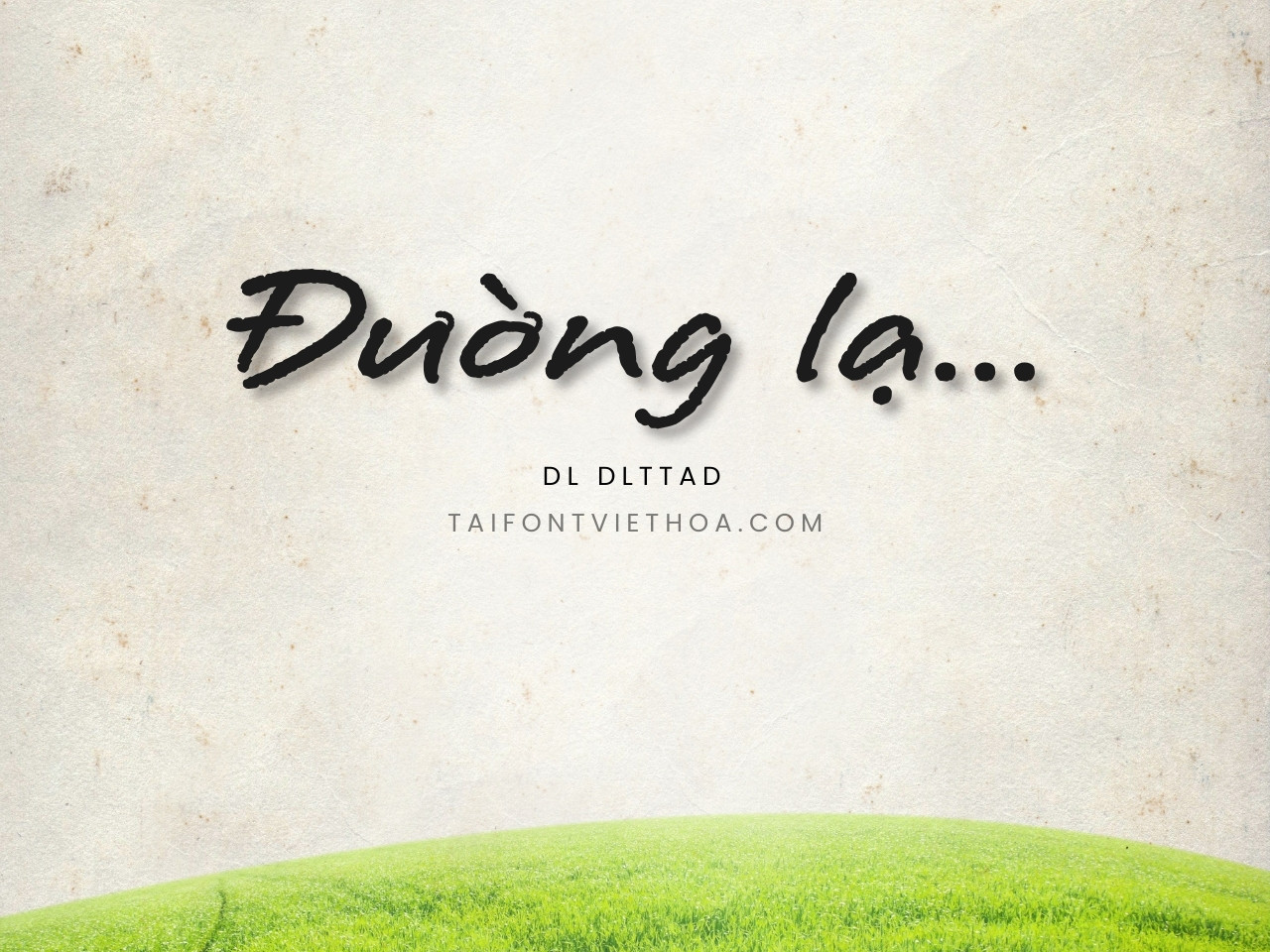
Giới thiệu về font DL Đừng Làm Trái Tim Anh Đau và bản Việt hóa
DL Đừng Làm Trái Tim Anh Đau là một font chữ viết tay (handwritten script) mang đậm dấu ấn tình cảm, được thiết kế theo phong cách cá nhân hóa với đường nét mềm mại, bay bổng như những lời nhắn nhủ ngọt ngào. Tuy không có bản gốc trên các kho font quốc tế, nhưng phiên bản này được phát triển và Việt hóa dành riêng cho người dùng Việt Nam, mang lại trải nghiệm trọn vẹn với bộ ký tự tiếng Việt đầy đủ và chuẩn Unicode.
Font được Việt hóa bởi cộng đồng đam mê typography, hướng đến đối tượng người dùng sáng tạo trong lĩnh vực nghệ thuật, in ấn cá nhân hoặc các thiết kế mang yếu tố cảm xúc. DL Đừng Làm Trái Tim Anh Đau được taifontviethoa.com sưu tầm, kiểm duyệt kỹ lưỡng và chia sẻ lại để phục vụ cho các dự án cần sự đồng cảm, bay bổng và đậm chất cá nhân. Font hỗ trợ tốt bảng chữ cái tiếng Việt, ký tự đặc biệt và được ứng dụng linh hoạt trong nhiều ngữ cảnh thiết kế hiện đại.
Đặc điểm thiết kế và ứng dụng thực tiễn
Font DL Đừng Làm Trái Tim Anh Đau sở hữu cấu trúc chữ tự do, các nét bút uyển chuyển như được viết từ tay thật, tạo nên cảm giác gần gũi, nhẹ nhàng. Tỷ lệ chữ mềm mại, độ nghiêng vừa phải, kết hợp các ligature tự nhiên giúp cho văn bản mang lại cảm giác trôi chảy và giàu biểu cảm. Font không quá cầu kỳ nhưng có điểm nhấn độc đáo ở cách thể hiện cảm xúc qua từng ký tự.
DL Đừng Làm Trái Tim Anh Đau đặc biệt phù hợp với các thiết kế về tình yêu, thiệp cưới, lời chúc, ảnh quote cá nhân, bìa sách truyện lãng mạn hoặc những chiến dịch quảng bá cảm xúc trong ngành thực phẩm, spa, quà tặng. Đây cũng là một lựa chọn hoàn hảo cho các nhà thiết kế muốn truyền tải cảm giác chân thật, bay bổng và tinh tế đến người xem.